总台蛇年春晚主标识发布,字体设计引人注目
蛟龙去,灵蛇来。11月29日,中央广播电视总台《2025年春节联欢晚会》发布主题和主标识。乙巳蛇年春晚将在欢乐吉祥、喜气洋洋的总基调中,以“巳巳如意,生生不息”为主题,与全球华人相约除夕、欢度农历新年。
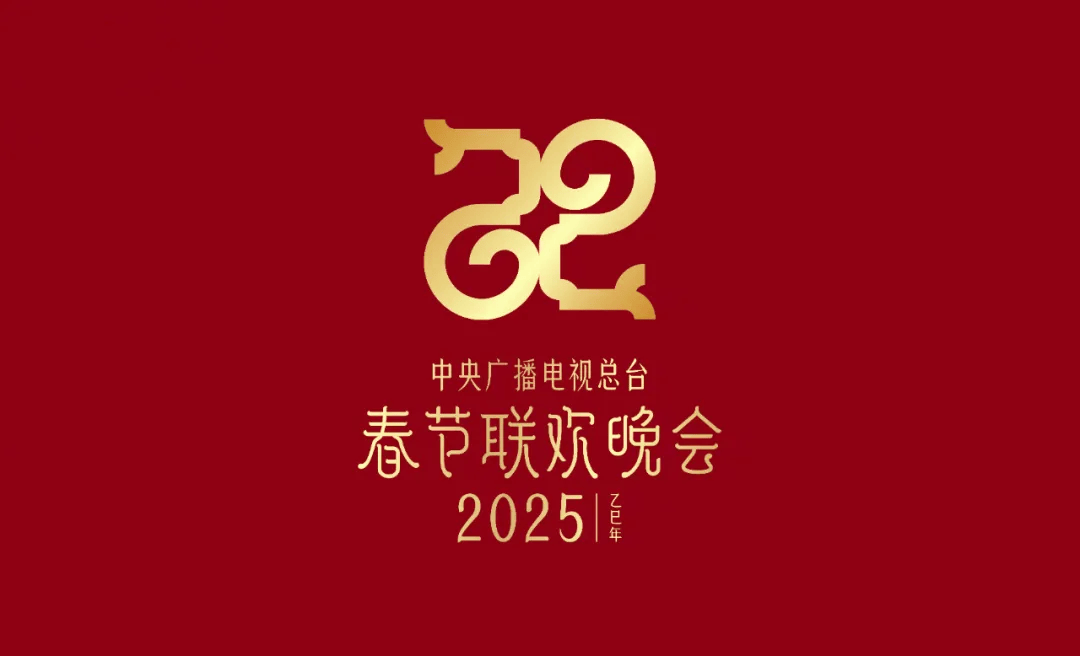
巳巳如意 生生不息 承古拓今 饱含深意
巳,象征着阳气巳出,阴气巳藏,万物见,成文章。而将两个“巳”字对称摆放,则恰似中国传统的如意纹样。双巳合璧,事事如意,这是乙巳蛇年与如意之间吉祥曼妙的创意链接,饱含喜庆美满的家国祝福,更彰显着中华民族精神根脉生生不息的时代力量。
总台蛇年春晚将在辞旧迎新的除夕夜,为全球华人献上巳巳如意的祝福,共同迎接一个温暖、欢乐的乙巳蛇年。
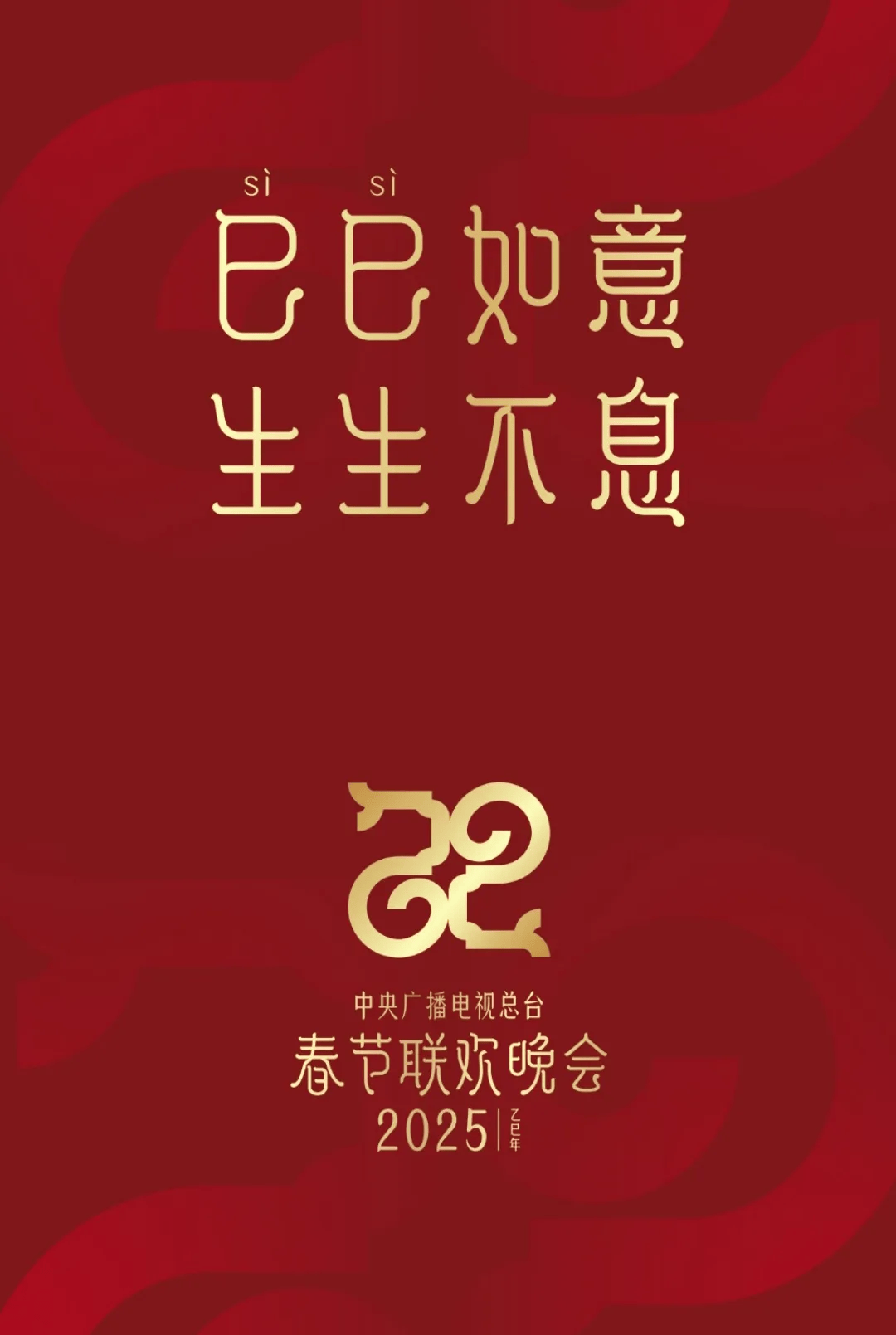
几幅壁纸同时发布
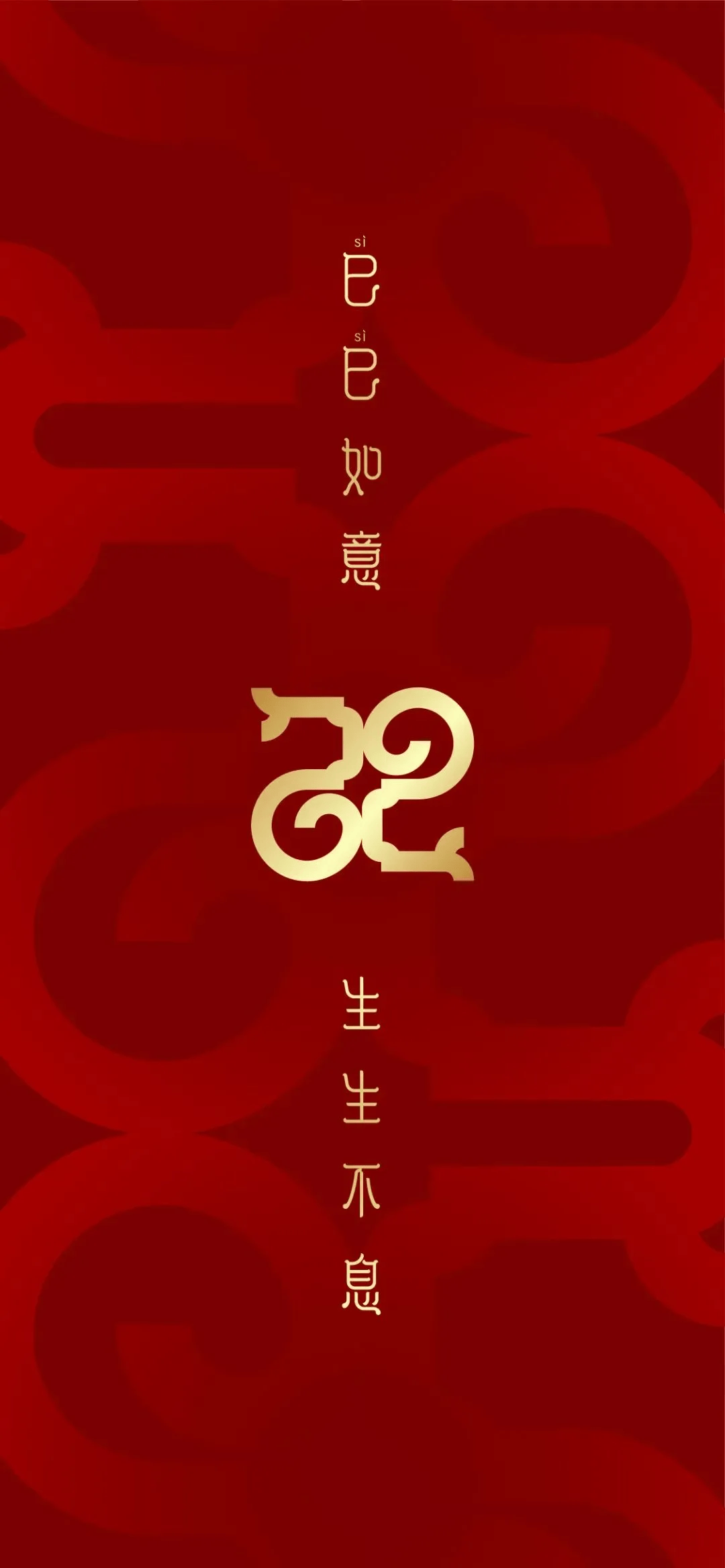
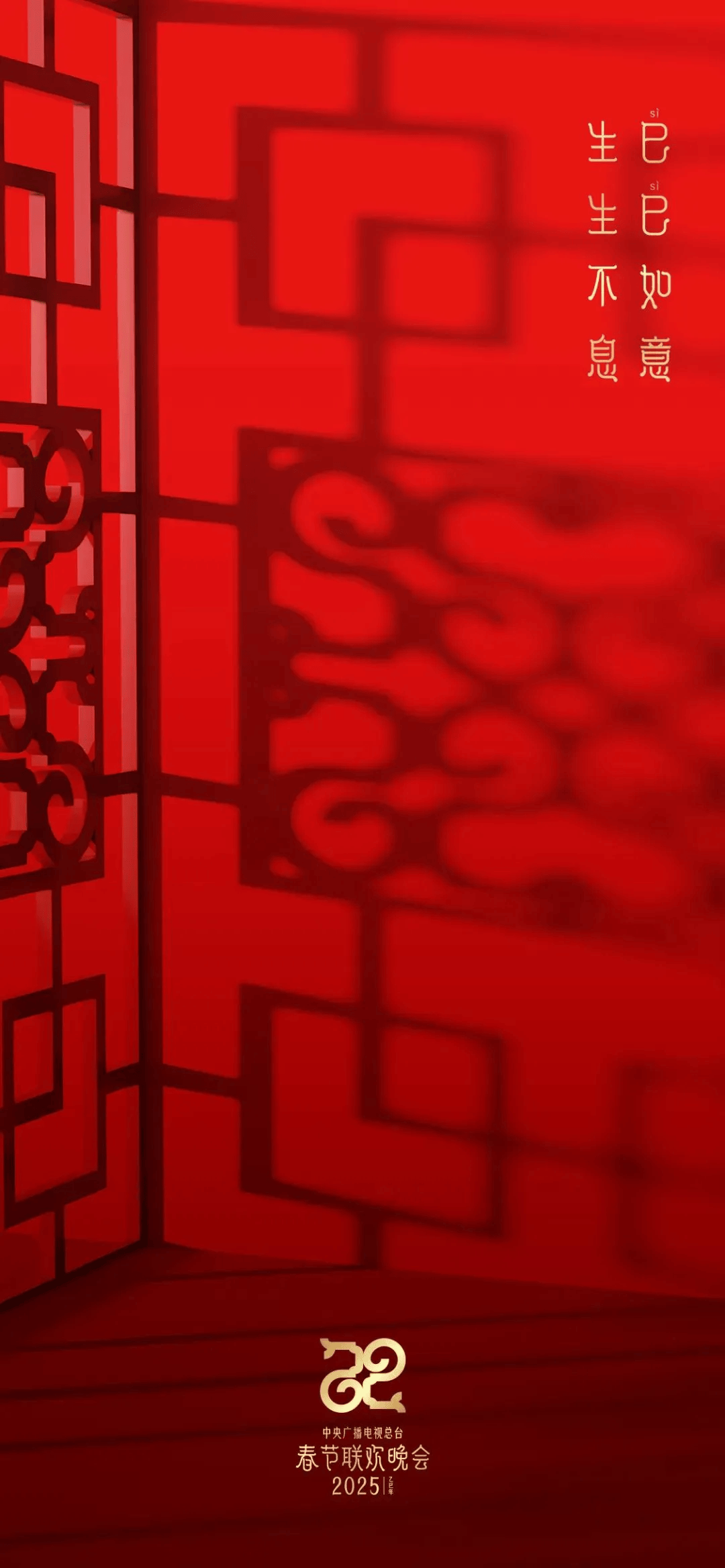
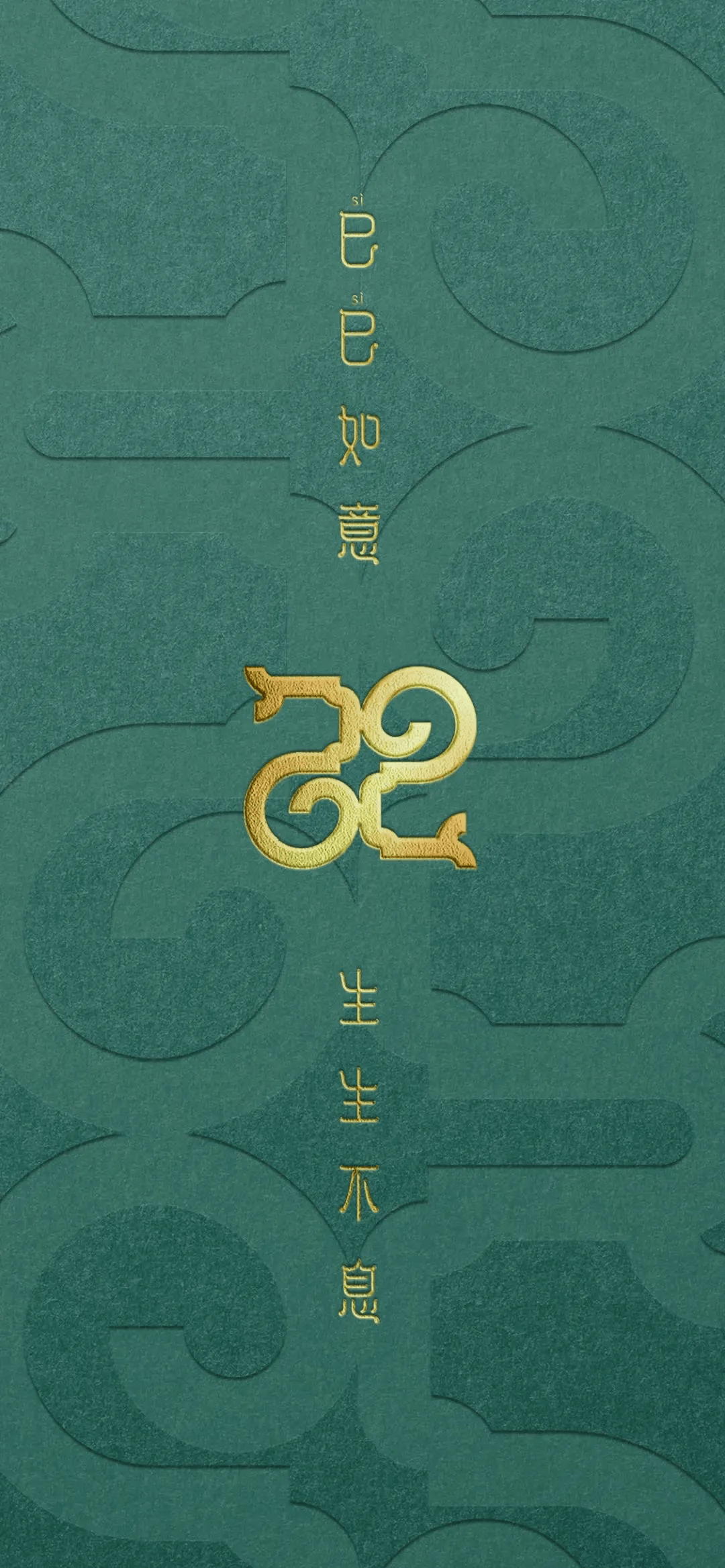
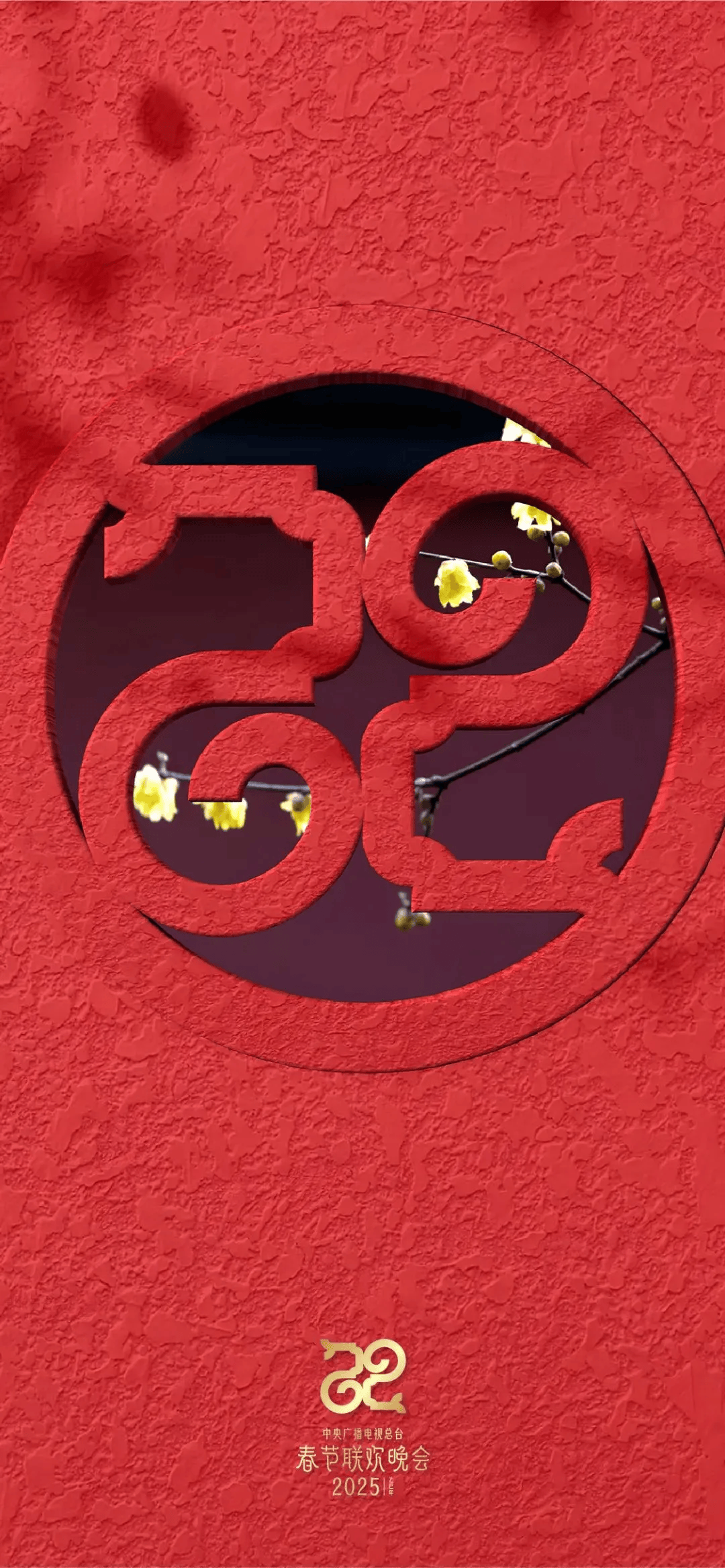
来回顾一下近几年春晚logo